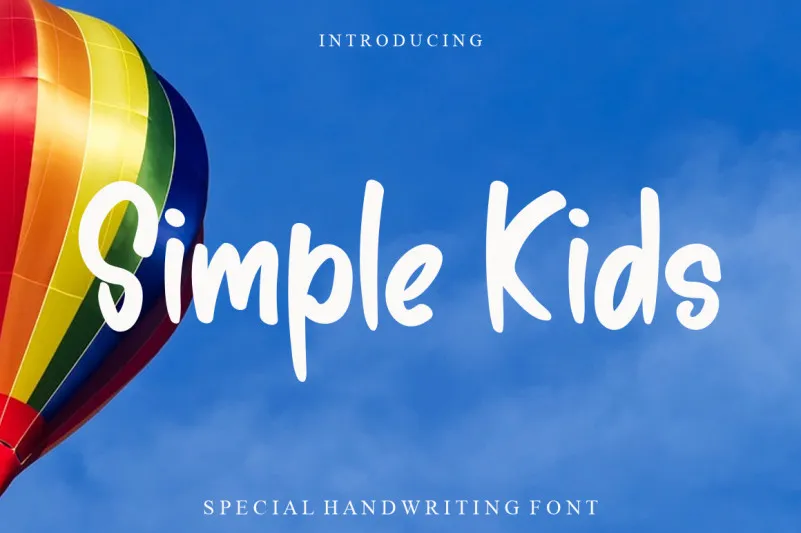
Simple Kids Font – Download Grátis
A fonte ‘Simple Kids Font’ do designer LevinCreative é uma seleção única para designers apaixonados por criar designs alegres e românticos. Ela é uma tipografia de escrever com pincel, convidativa à ser usada em um range amplo de ideias de design. Esta fonte tem um aspecto delicado e genuíno, desenhada como letra cursiva escrita a mão. É perfeitamente adequada para adicionar um toque leve e encantador a qualquer projeto, garantindo que seu design brilhe em uma ampla gama de ideias, desde cartões de aniversário até cartazes e até mesmo em elementos gráficos infantis. A ‘Simple Kids Font’ se destaca não apenas pela sua elegância, mas também por ser um recurso conveniente para designers buscando simplificar o processo criativo sem sacrificar a qualidade visual ou personalidade do design.